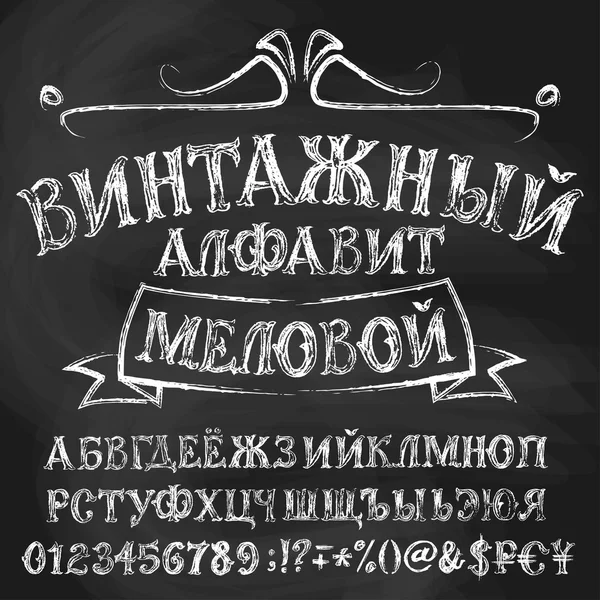
Замечательные стили с эффектом надписей на школьной доске.
Шрифт Chalk SVG
Являетесь ли вы художником по надписям, дизайнером или нет, вы можете легко делать цитаты мелом и создавать композиции из букв на доске. Теперь вам не нужно строить каждую букву по правилам, делать из нее отдельный дизайн, наносить фактуру мела. Здесь вы можете скачать набор фактурных меловых шрифтов, которые одним прикосновением пальца решат любую задачу. Он поставляется в 4 различных стилях: Solid, Shape, Deco, Deco2.